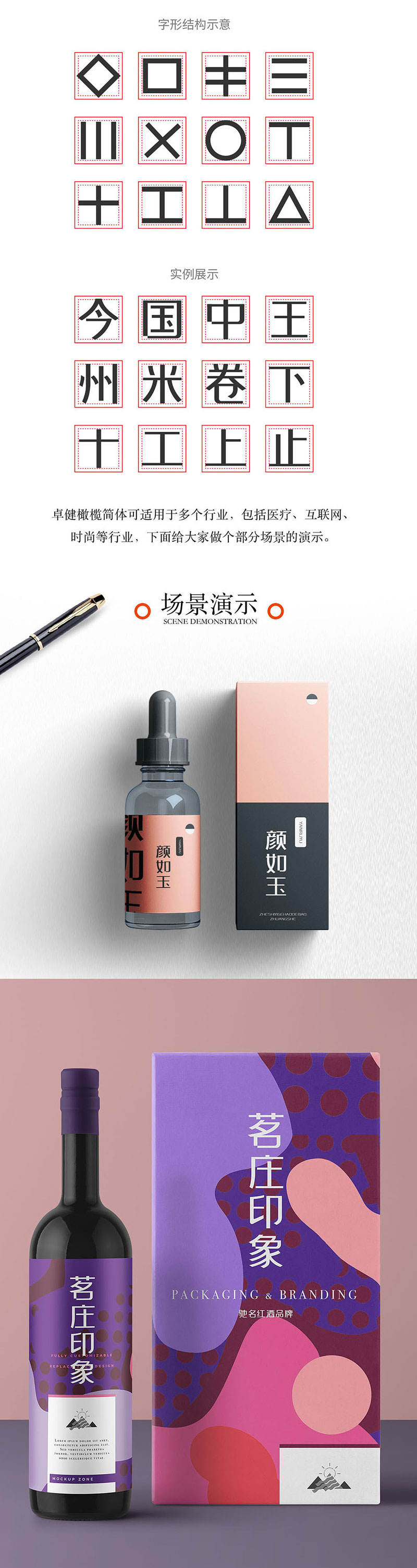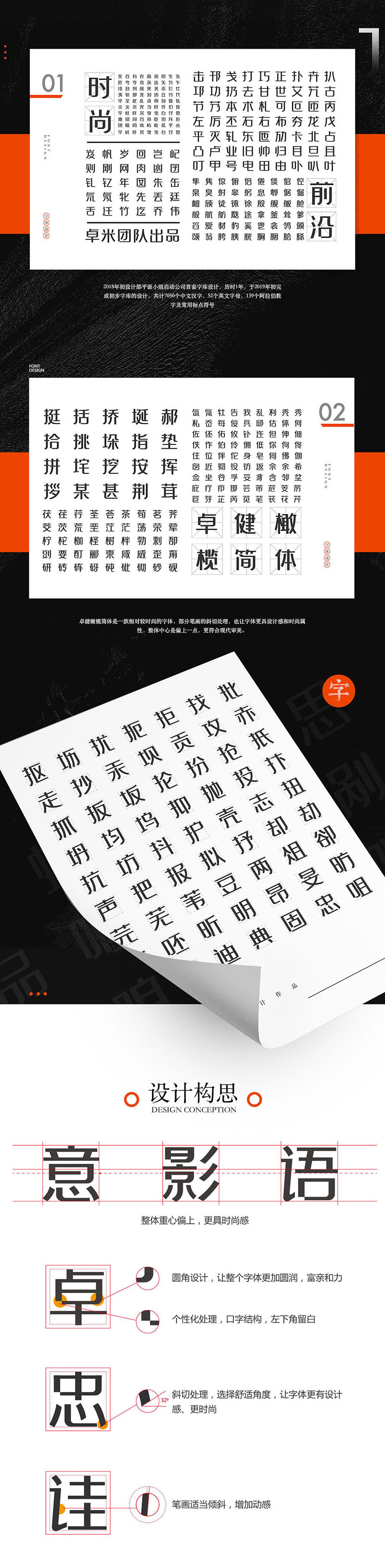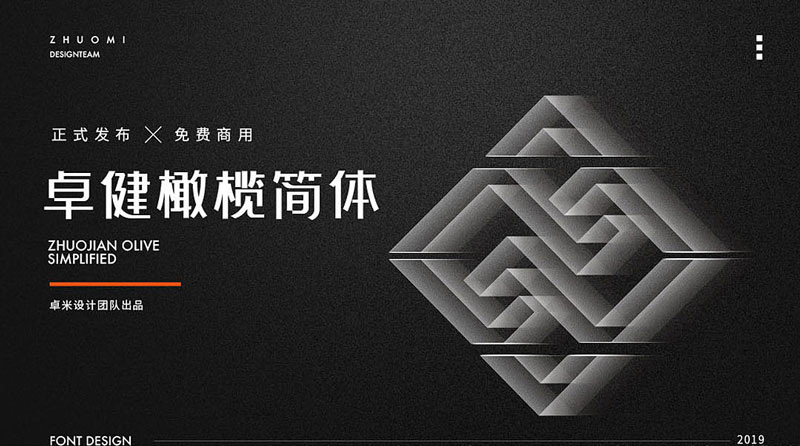
卓健橄榄简体免费商用
卓健橄榄简体是由卓健设计团队制作,是一款相对较时尚的字体,部分笔画的斜切处理,也让字体更具设计感和时尚属性,整体中心是偏上一点,更符合现代审美。字体圆角设计,让整个字体更加圆润,富亲和力。口字结构,左下角留白,个性化处理更具特色。字库共7050个常用字,感谢卓健设计团队的分享。
卓健橄榄简体